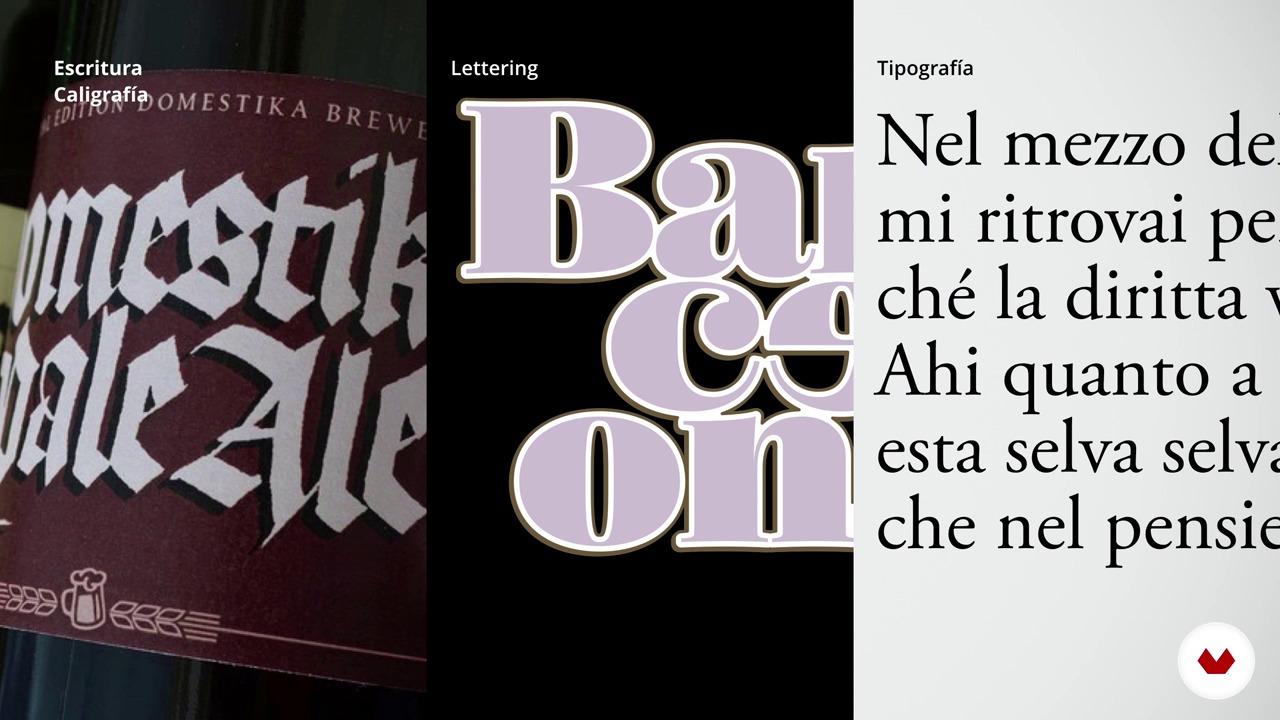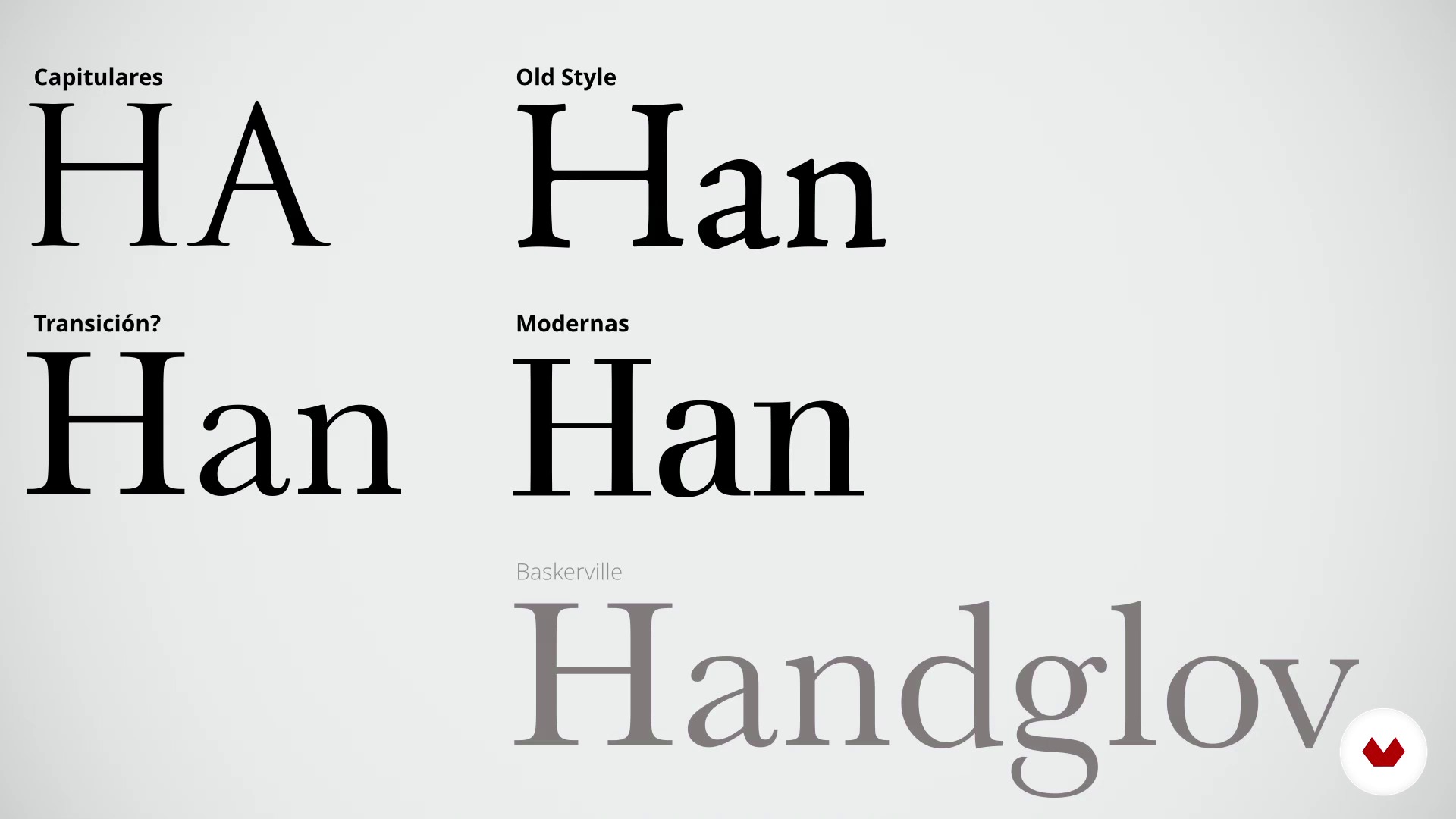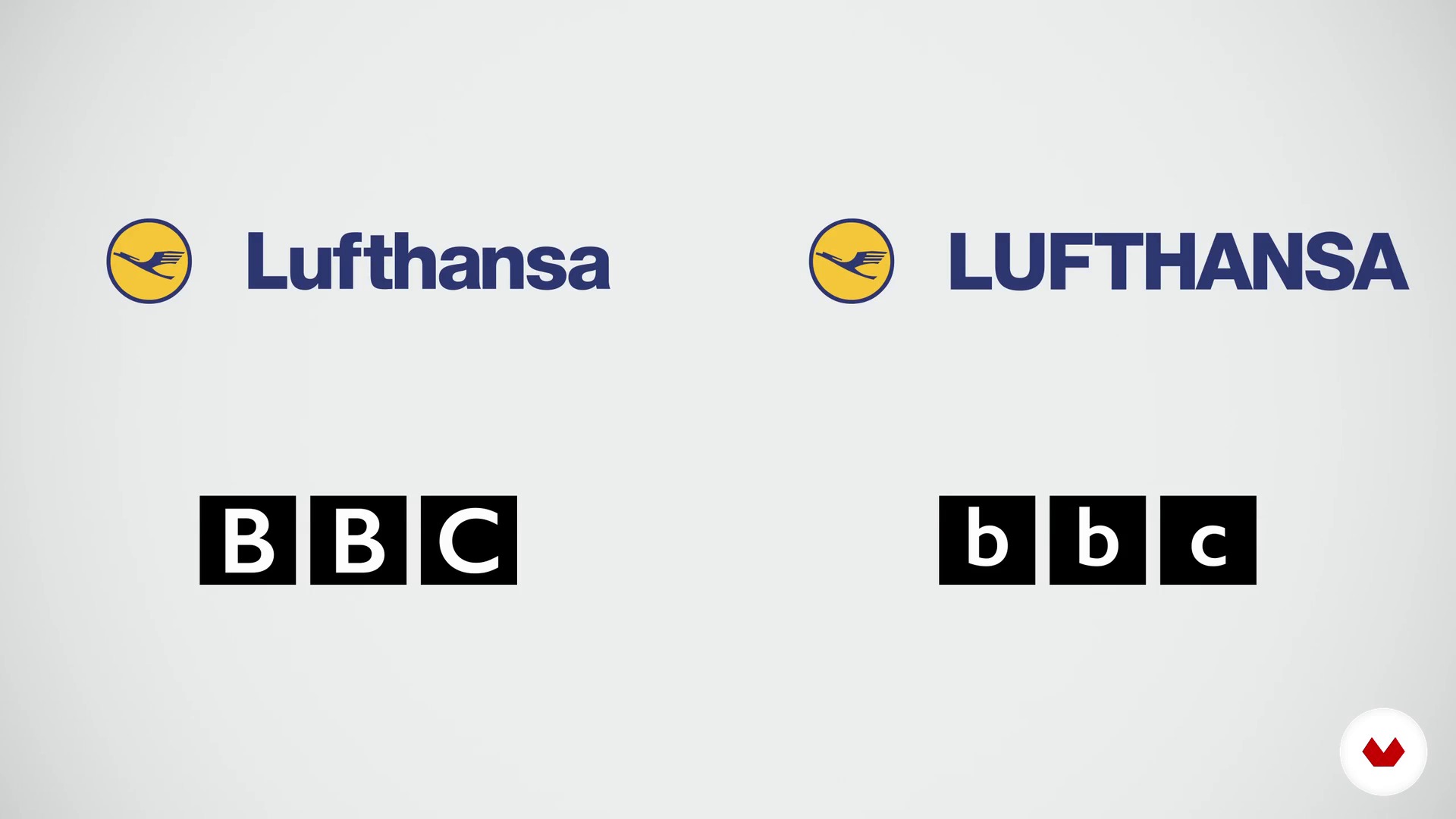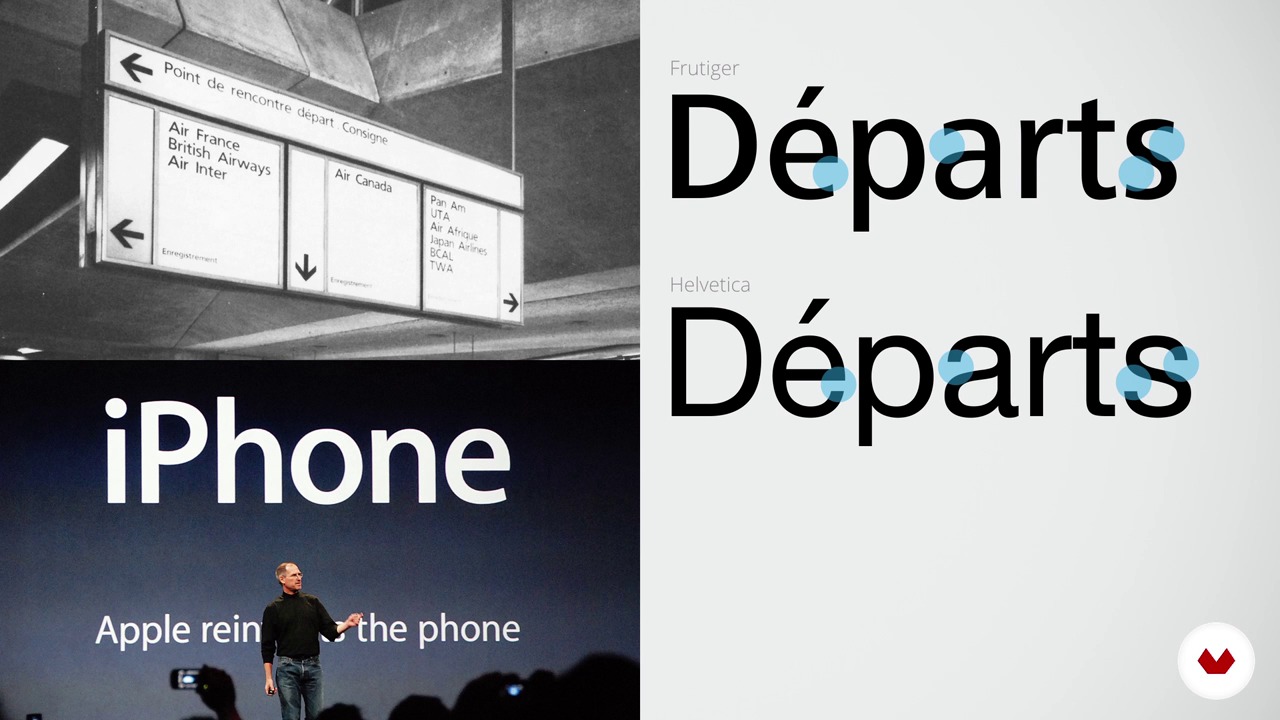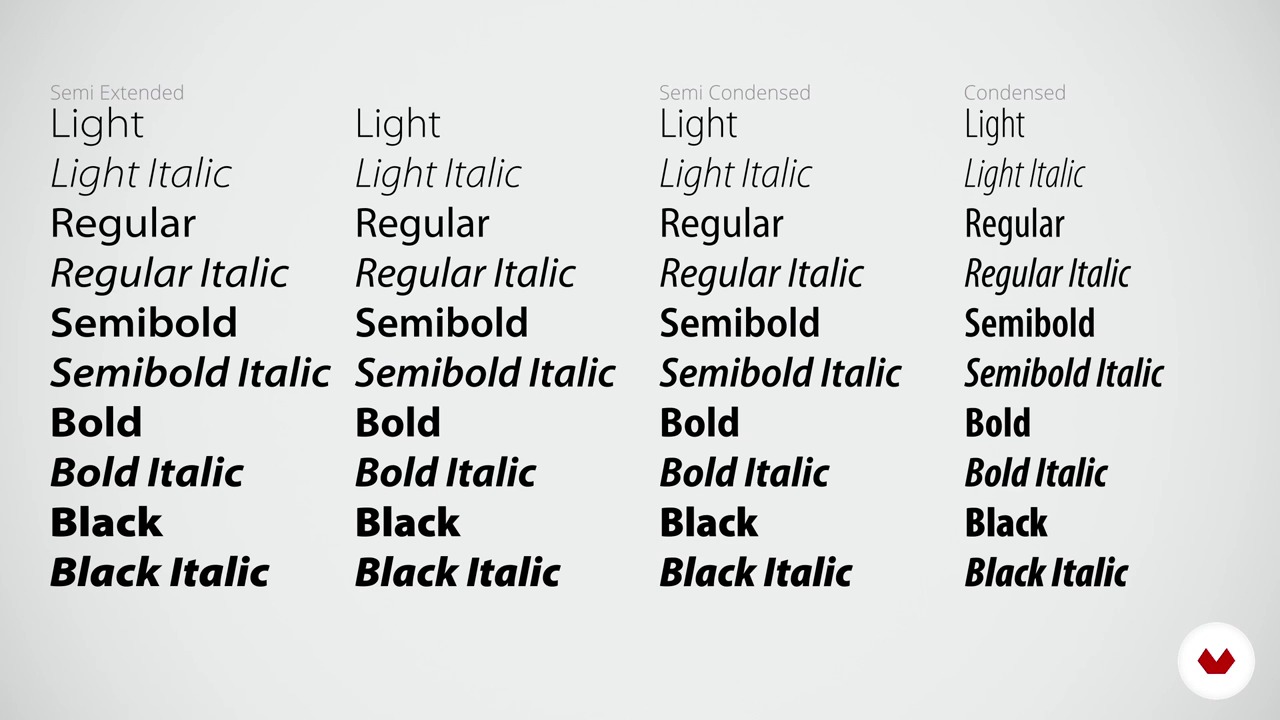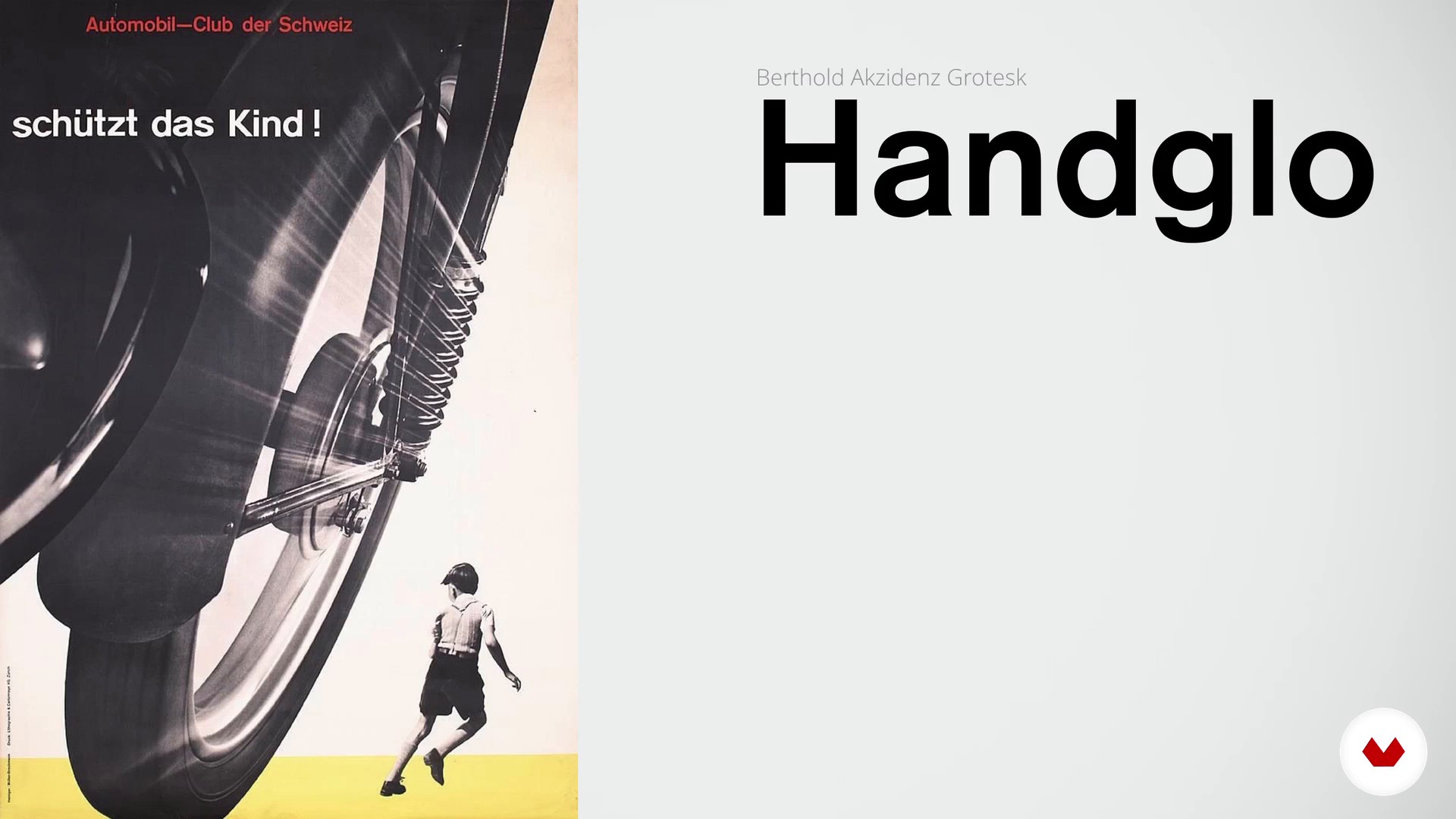
Enric Jardí é designer gráfico, especialista em tipografia e design editorial. Neste curso, você aprenderá como, por que e de que maneira escolher as fontes mais adequadas para seus projetos. Enric irá explicar como trabalhar com eles, mostrando os erros mais comuns cometidos ao usá-los e como evitá-los.
Você aprenderá a usar as letras, não para projetá-las. Enric vai ensiná-lo a olhar para eles de uma nova maneira, sem longas listas sobre suas partes e classificações, mas entendendo a sua origem e por que são assim, conhecendo as razões para escolhê-las, como combiná-las, como obtê-las e gerenciá-las.
Você se tornará um especialista selecionando fontes de A a Z.
Você vai começar a conhecer um pouco mais sobre o trabalho e as influências de Enric Jardí.
Então você aprenderá a analisar um texto entendendo como isso é feito e se você pode manipulá-lo distinguindo se o texto é editável.
Então você aprenderá os principais conceitos sobre legibilidade, maiúsculas, minúsculas, grandes e pequenos textos. Você descobrirá as diferentes famílias tipográficas que existem e entrará na história das letras do século XX e nos caracteres do alfabeto. Além disso, Enric irá gastar algum tempo explicando os melhores tipos de papel e tela.
Neste ponto, você saberá o que "nos diz" cada tipografia como observadores, como combiná-los, trabalhar em OpenType e dicas para evitar. Antes de terminar, você também verá vários trabalhos reais e você saberá algumas considerações práticas e legais sobre o gerenciamento de fontes em seu computador que virão a você muito bem para o seu dia a dia profissional.
Seguindo tudo o que aprendemos durante o curso, você deve escolher uma série de tipografias para a publicação de um jornal que trabalhe com uma estrutura hierárquica complexa e flexível.
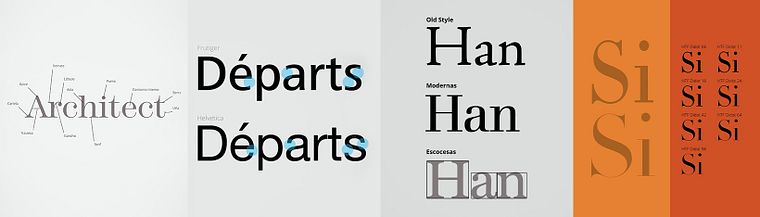
Este curso destina-se tanto a profissionais de design gráfico como ao mundo editorial que trabalham todos os dias com tipografia, seja em mídia impressa ou digital, bem como aqueles que, sem ter muita experiência no assunto, querem aprender um pouco mais sobre tipografia e seu funcionamento.
Embora alguns conselhos sejam dados sobre como lidar com texto no InDesign, no Illustrator e no gerenciamento de fontes no Macintosh OS que serão úteis para designers gráficos profissionais, nenhum conhecimento especial em tipografia é necessário.
Você vai aprender a selecionar, combinar e aplicar tipografias em projetos editoriais, criar hierarquia visual, melhorar a legibilidade e desenvolver critérios para escolher fontes adequadas para livros, revistas, jornais, capas e branding.
Vai aprender a criar sistemas tipográficos hierárquicos para organizar informações, definir estilos para títulos, subtítulos e corpo de texto, e melhorar a legibilidade em publicações periódicas.
Sim, o curso ensina critérios para escolher e combinar tipografias na criação de logos, identidade visual e elementos de branding, levando em conta tendências e coerência na comunicação.
O curso diferencia cada área: tipografia como design de letras digitais, rotulação como letras desenhadas, caligrafia como escrita manual e lettering como composição artística de letras.